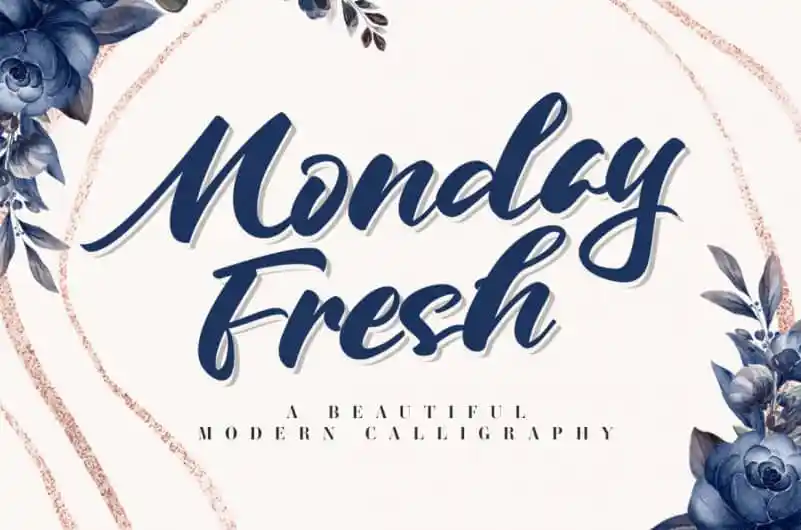
Monday Fresh Calligraphy Font – Download Grátis
A Monday Fresh Calligraphy Font é perfeitamente apropriada para criar um visual elegante em diferentes formatos de mídia, desde embalagens até sites de redes sociais e perfis de casamentos. Seu estilo fresco e suave proporciona uma identidade visual única que pode expressar mensagens em destaque, tornando-a perfeita para diversos projetos. Suas linhas delicadas são ideais para personalizar anúncios, capas de livros ou qualquer outra peça de design que exija um toque elegante e atraente. Seja você um estilista criativo buscando uma fonte única para embalagens de cosméticos, um designer web em busca de um novo tipoface para sites e redes sociais, ou simplesmente alguém querendo adicionar personalidade a seu texto para eventos especiais como casamentos, esta fonte é perfeita. Sem dúvidas, ela fará sua marca mais chamativa.
Designer: agniardi